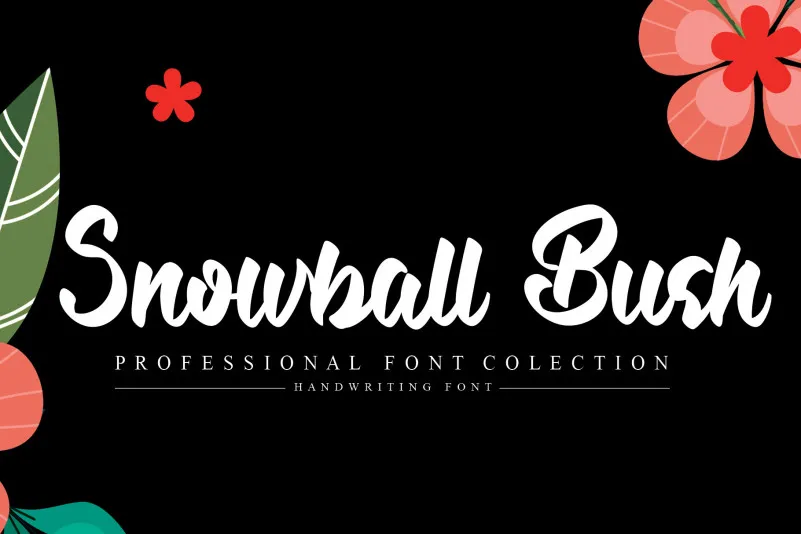
Snowball Bush Script Font é uma elegante tipografia script que traz um toque sofisticado a qualquer projeto design. Perfeita para criar cartões de convite de casamento, cartas de gratidão, cartazes de boas-vindas e até mesmo logomarcas ou identidades empresariais, esta fonte tem o poder de dar uma personalidade única ao seu trabalho. E embora seja ideal para qualquer projeto que necessite de uma sensação de escrita a mão, é especialmente indicada para criações com um toque romântico e delicado. Sua facilidade em manuseio a torna uma fonte versátil e indispensável no acervo do designer moderno. Com Snowball Bush Script Font, suas criações serão ainda mais únicas e autênticas, destacando-se perfeitamente nas mais diversas aplicações de design.